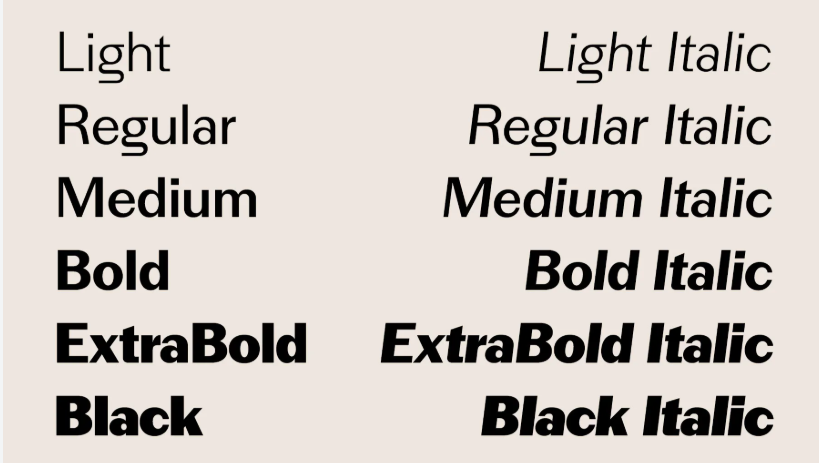
Picaresk Font Việt hóa là bộ phông chữ thuộc dòng Display Serif mang phong cách nghệ thuật đương đại (Avant-Garde) đầy táo bạo, sắc sảo và mang đậm hơi thở thời trang cao cấp. Với cấu trúc chữ kéo dài thanh lịch, các đường chân chữ sắc lẹm kết hợp cùng độ tương phản nét thanh đậm tột đỉnh, phông chữ này là lựa chọn đỉnh cao cho các thiết kế logo thời trang xa xỉ, nhãn chai nước hoa, bìa tạp chí nghệ thuật và bao bì hộp quà tặng thượng lưu. Doozypack.vn cung cấp link tải Picaresk Font Family Việt hóa trọn bộ chuẩn kỹ thuật, giúp bạn sở hữu phông chữ đẳng cấp này, hỗ trợ đầy đủ tiếng Việt để tự tin thiết kế bao bì và bộ nhận diện thương hiệu chuyên nghiệp.
Đặc điểm thẩm mỹ độc đáo của bộ font Picaresk
Picaresk không đi theo sự an toàn của các phông chữ có chân truyền thống; nó mang đến một ngôn ngữ thị giác đầy tính tiền phong (avant-garde), phá vỡ mọi quy chuẩn thông thường để tạo nên vẻ đẹp sang trọng và nổi loạn.
Phong cách Avant-Garde sắc sảo và mang hơi thở tạp chí cao cấp
Đặc trưng lớn nhất của Picaresk Font Việt hóa là sự kết hợp giữa tỷ lệ hình học kéo dài theo chiều dọc và các góc cắt sắc lẹm. Cấu trúc chữ gợi liên tưởng đến những bộ sưu tập thời trang haute couture trên các sàn diễn Paris, mang lại cảm giác kiêu kỳ, sắc lạnh và vô cùng đắt giá. Khi đặt Picaresk làm tiêu đề trên bao bì, sản phẩm của bạn sẽ ngay lập tức toát lên vẻ thượng lưu, cá tính và có chiều sâu nghệ thuật tuyệt đối.
Cấu trúc chữ kéo dài kiêu kỳ với độ tương phản nét hoàn mỹ
Các ký tự trong trọn bộ Picaresk Font Family sở hữu nét dọc dày dặn đối lập hoàn hảo cùng các nét ngang thanh mảnh như sợi tơ (hairline). Trục chữ thẳng đứng kiêu hãnh cùng khoảng cách chữ ôm sát tạo nên nhịp điệu Typography vô cùng ngăn nắp, giúp tôn vinh tối đa tên thương hiệu trên các bề mặt vỏ hộp.
Ưu điểm nổi bật của bản Picaresk Font Family Việt hóa
Khi ứng dụng các phông chữ thời trang quốc tế vào thị trường trong nước, sự chỉn chu về dấu câu là yếu tố quyết định đến tính chuyên nghiệp của ấn phẩm:
- Khắc phục triệt để lỗi dấu tiếng Việt: Phiên bản Việt hóa đã được đội ngũ thiết kế trau chuốt thủ công từng dấu câu. Các dấu sắc, huyền, hỏi, ngã, nặng được vẽ với tỷ lệ cân đối, đặt ở vị trí thoáng đãng so với thân chữ, không gây cảm giác chắp vá hay đè nét làm mất tính thẩm mỹ avant-garde.
- Kiểm soát độ dày nét Hairline khi gia công: Các nét ngang và điểm chuyển nét của font chữ này khá mảnh. Khi gia công ép kim vàng (Hot Stamping) hoặc dập nổi, designer nên đảm bảo nét chữ có độ dày tối thiểu 0.15mm để nhũ bám dính sắc nét, không bị đứt đoạn.